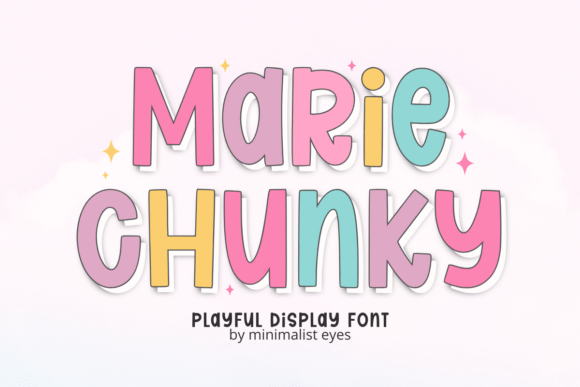
Marie Chunky
適切なデザイン要素を見つけるのは難しい場合がありますが、Marie Chunkyは作品を即座に引き立てる優れたコレクションを提供します。
POD(オンデマンド印刷)製品、結婚式の招待状、またはソーシャルメディアのグラフィックを作成している場合でも、Marie Chunkyは理想的です。